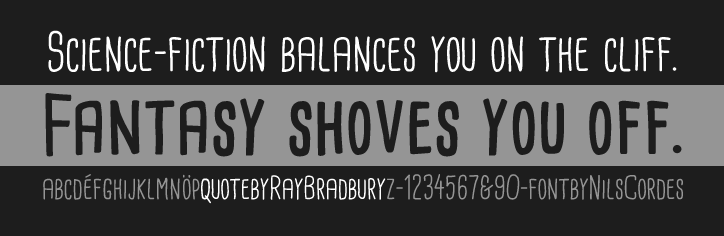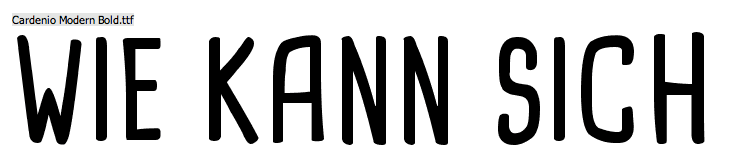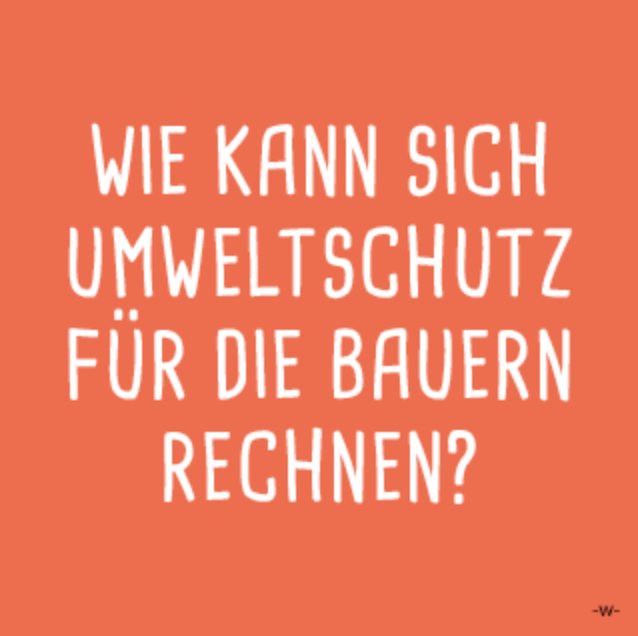
Kennt jemand diese Schrift? (Umweltschutz)
Welche Schrift könnte das sein?
diese Schrift habe ich aus einer Anzeige.
Ich meine das war der WWF. Die benutzen diese aber nicht als Hausschrift.
Habe auch über WhatTheFont (erfolglos) gesucht.
Ja es gibt so viele.
Ich werde das Projekt vorerst mit der "Moon Flower" machen.
die Schrift kommt mir bekannt vor und ich schau mal kurz in meinem E-Katalog. Das sollte die Schrift Cardenia Modern von Nils Cordes sein ... in Großbuchstaben geschrieben ... sagen meine Unterlagen ... und die gibt es ... äh ... Moment ... ah ja ...
Moment! Canted Comic und Canted FX? Nils Cordes treibt sich doch auch hier rum?
Doch, doch, Uwe hat schon recht ... sind halt alles mal wieder nur Versalien.
Aber nur fast. Mindestens beim R wurden die Gemeinen verwendet. :-D